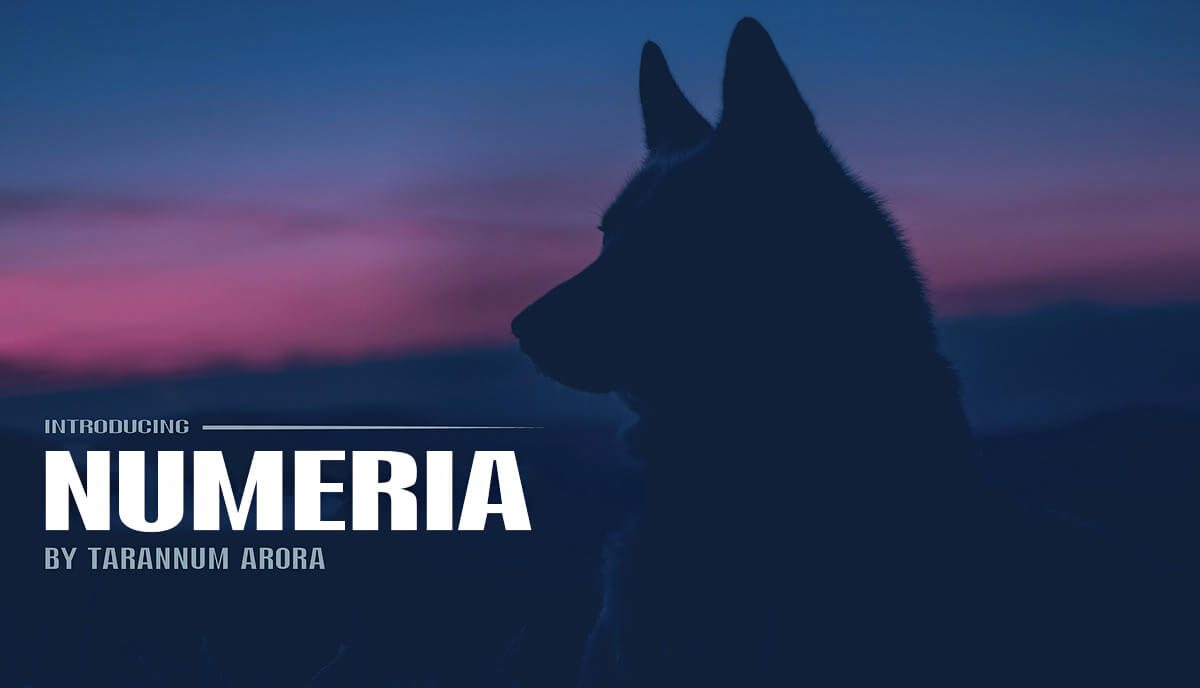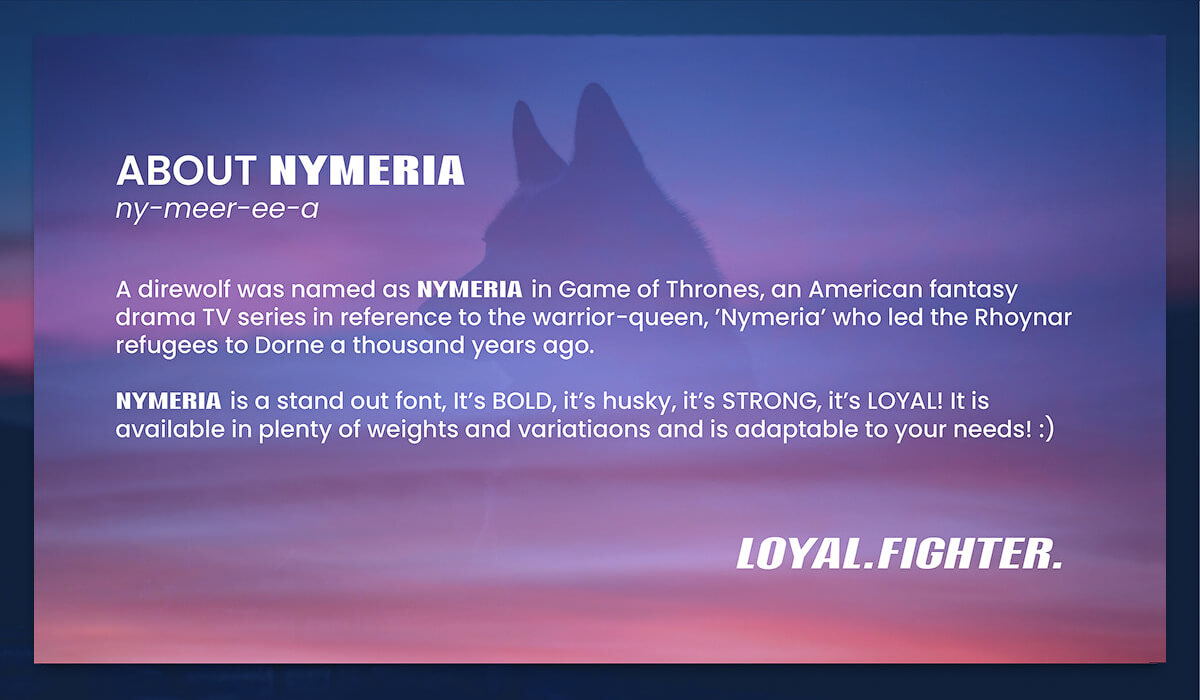
Шрифт - Nymeria
Этот элегантный и строгий шрифт, будет стильно выглядеть в ваших дизайнерских проектах. Семейство шрифтов Nymeria доступно в нескольких стилях, которые отличаются универсальностью как в печаnи, так и для медиа.